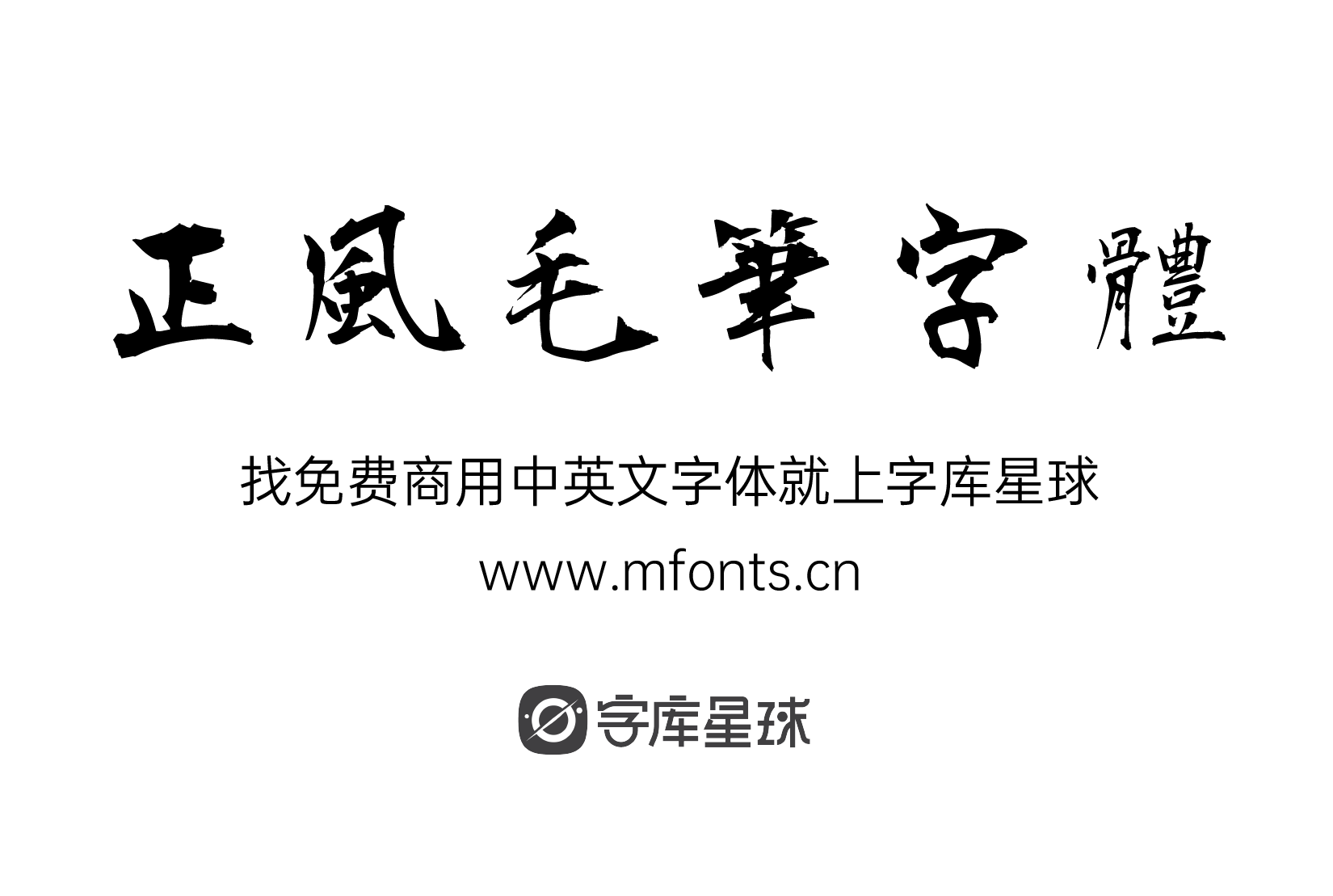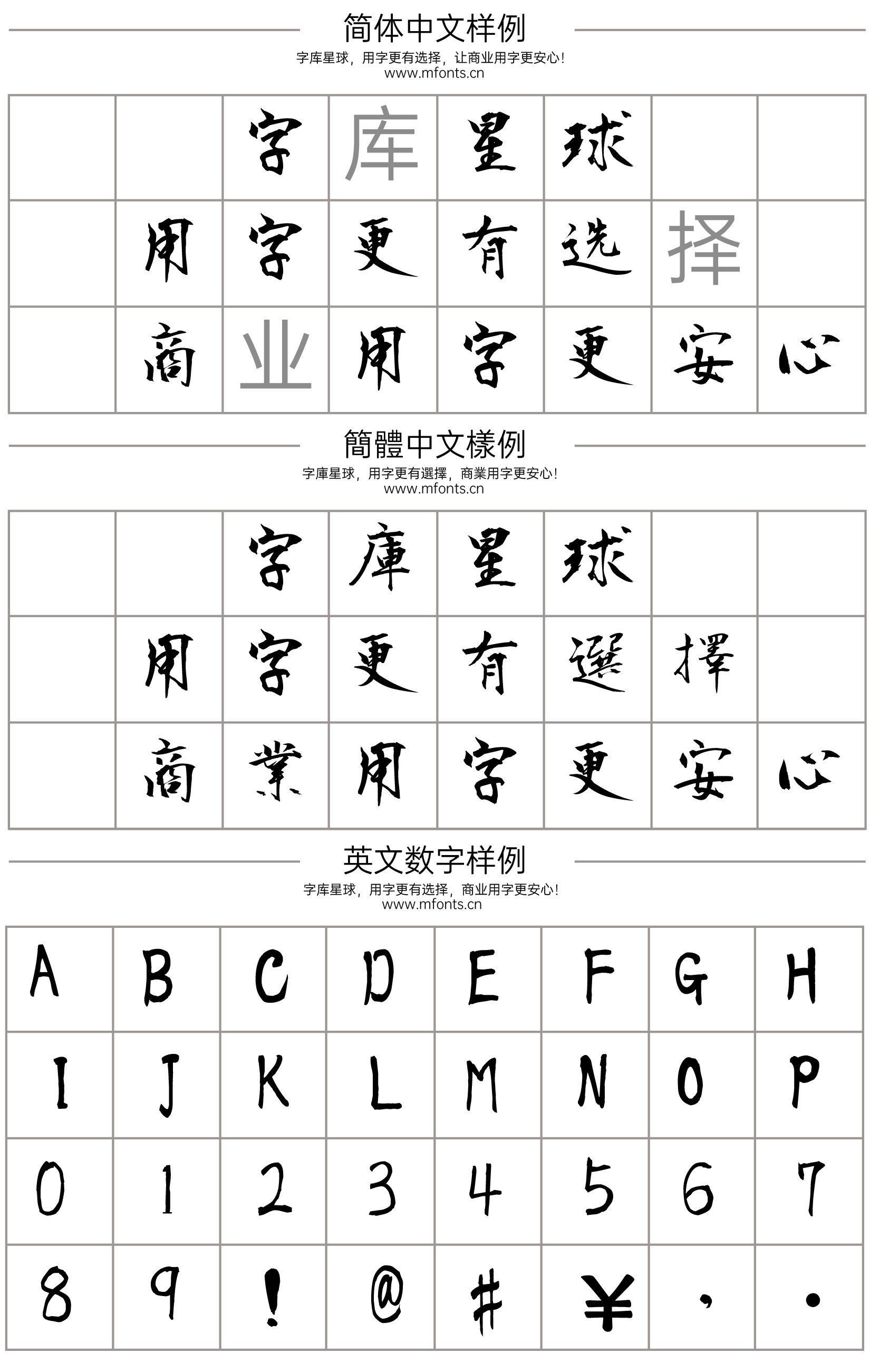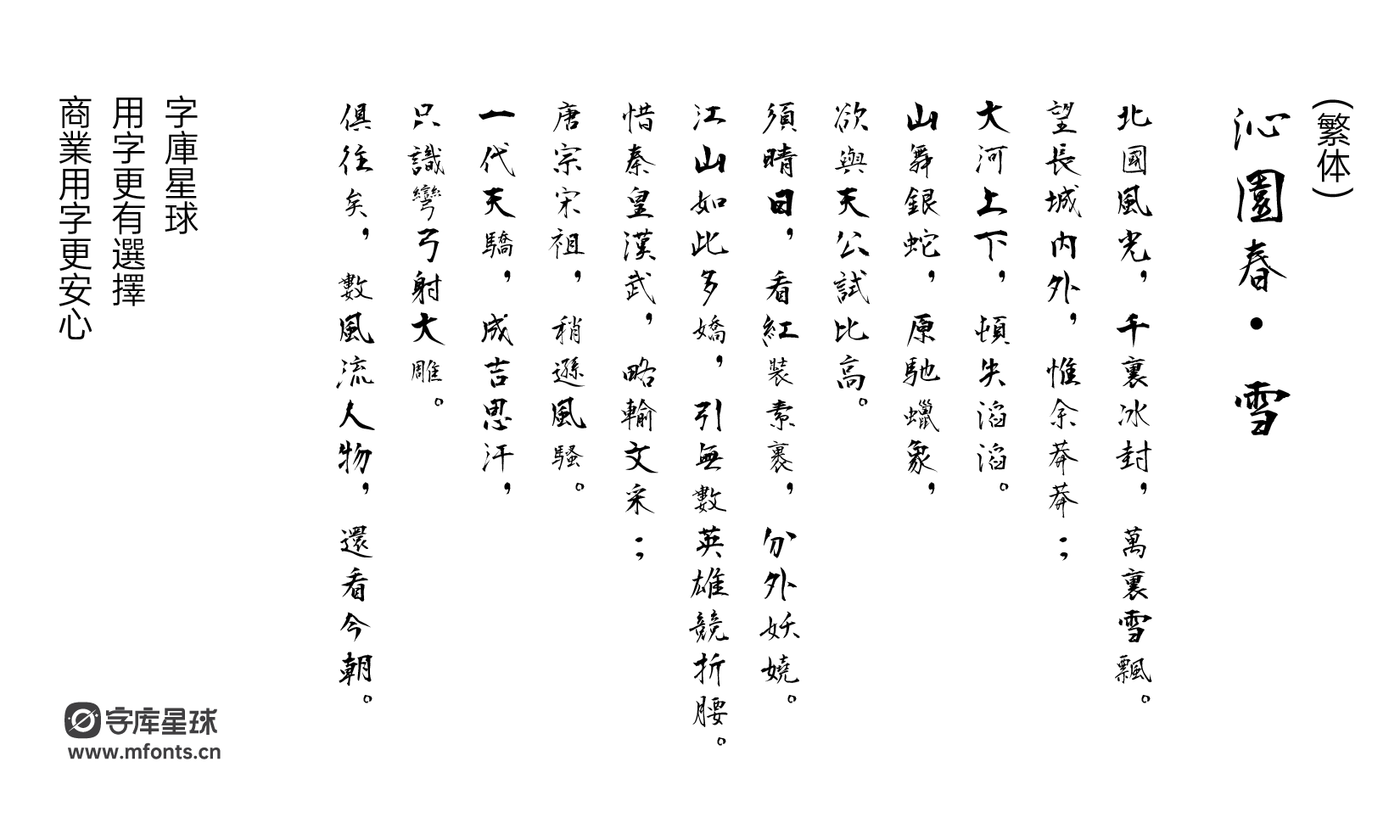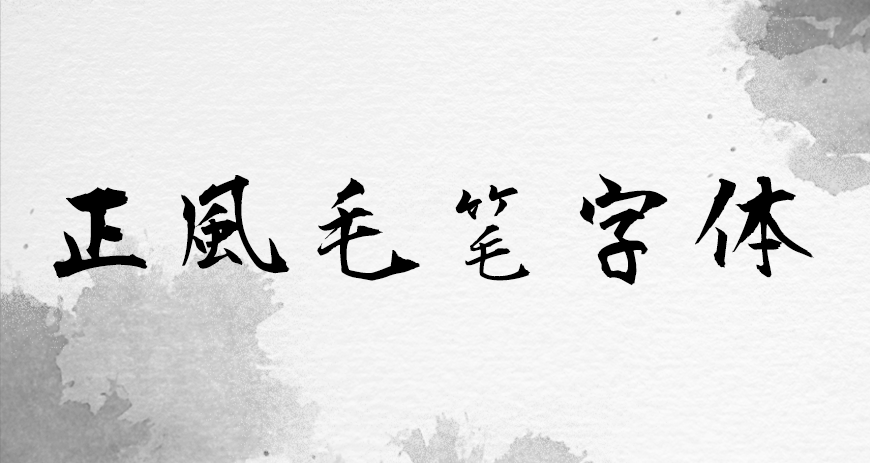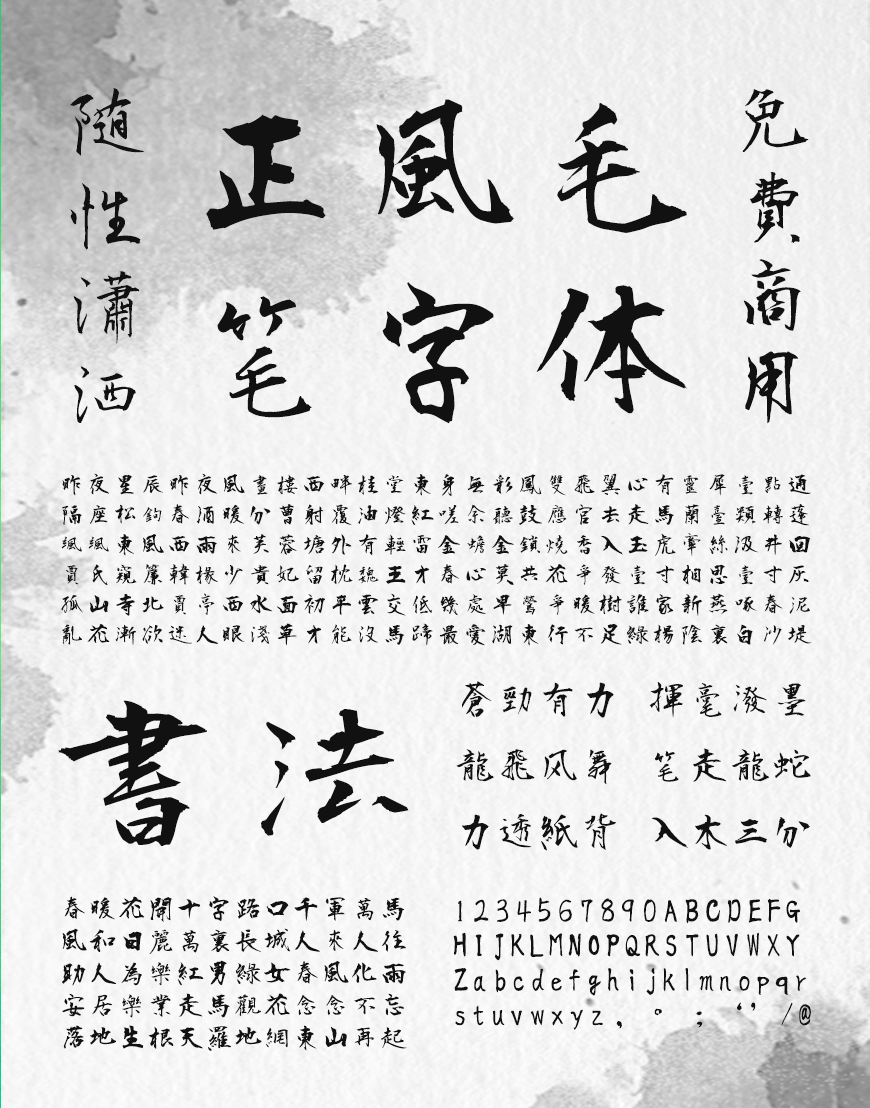
正风毛笔字体是中国台湾的设计师Max基于衡山毛笔行书进行字符增补的一款毛笔字体。
该字体修改前文字加符号数共7,582字,修改后文字加符号数共23,699字。第一阶段的补字已补齐中国台湾教育部列出的4,808个常用字,还是有些日常生活的常用字没有补到。
正风毛笔字体含有五个字重,字重越小,笔画的粗细对比也会更加明显,字重大则更加有力。
原本的衡山毛笔行书字体放在Regular字重里,通过程序自动产生ExtraLight、Light、Medium、Bold等新的字重,Light字重是把原本的衡山毛笔行书微微调细一点点,在ExtraLight的字重裡,可能会因为笔划太细造成某些笔画消失。
相较于正风毛笔字体的师兄莫大毛笔体,正风在个性上就随性很多,也造成有部份的一些字很粗,而有些字极细。原作者的“木”、“米”、“禾”系列常常会少一撇,是正常的,第一次看到会觉得有点怪,但是看久就会习惯了。
字体保留了毛笔书写留下的手写痕迹,在起笔、收笔、转折处会有明显的毛笔的痕迹,这使得字体更加接近手写的自然,有一种质朴感。